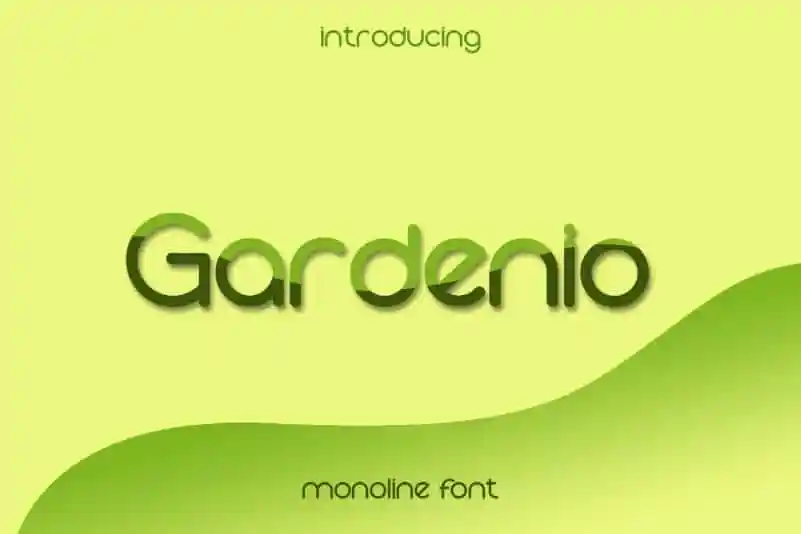
Gardenio Sans Serif Font – Fonte Grátis
Gardenio Sans Serif Font
A Gardenio Sans Serif Font é uma escolha perfeita para aqueles que buscam um equilíbrio entre elegância e modernidade. Com linhas monolineares, essa fonte sans serif exibe um estilo chic com um toque de nostalgia retro. É ideal para aplicações como logotipos e identidades corporativas em um enfoque moderno, tornando-a uma escolha ideal para revistas, capas de jornal, posters, identidade visual ou anúncios. Com sua simplicidade e beleza contemporânea, Gardenio é versátil o suficiente para atender a uma variedade de necessidades gráficas. Ideal tanto para designer profissional quanto para iniciantes que buscam estilizar seus materiais de maneira criativa. Não importa se você está trabalhando em um projeto editorial ou comercial, Gardenio pode oferecer aquele toque especial e inovador que seu design precisa.